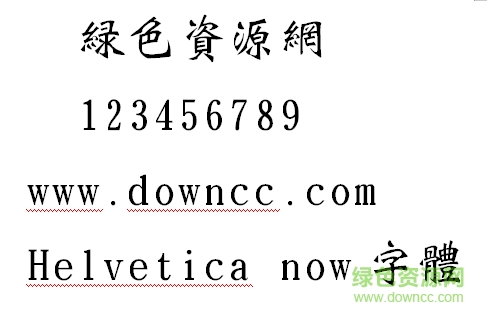
文鼎魏碑繁是文鼎字體庫中的一款魏碑繁體字體,筆畫偏粗,字形略圓,藝術(shù)設(shè)計(jì)會(huì)常用的。還適合用在多個(gè)不同領(lǐng)域,有需要的用戶趕快來下載體驗(yàn)吧!
筆意樸拙,不避鋒芒,規(guī)則中正
其風(fēng)格蒼勁堅(jiān)實(shí)
適用于文化類的宣傳設(shè)計(jì)
結(jié)構(gòu)跌宕起伏
以及商業(yè)類品牌的廣告和產(chǎn)品包裝設(shè)計(jì)